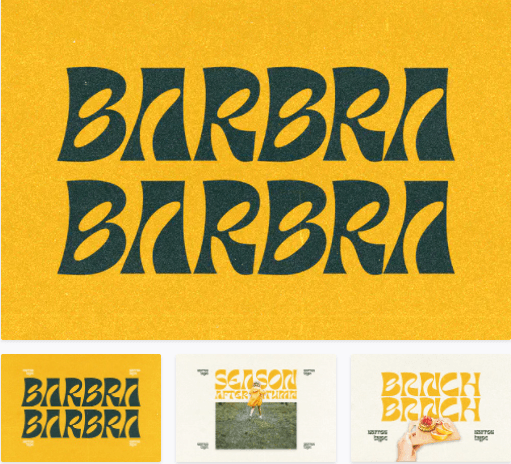
Barbra Font
Barbra - это семейство отображаемых шрифтов с уникальными формами букв и гармонизацией. Он жирный, но контрастный. Бруталист, но великолепный и эмоциональный.